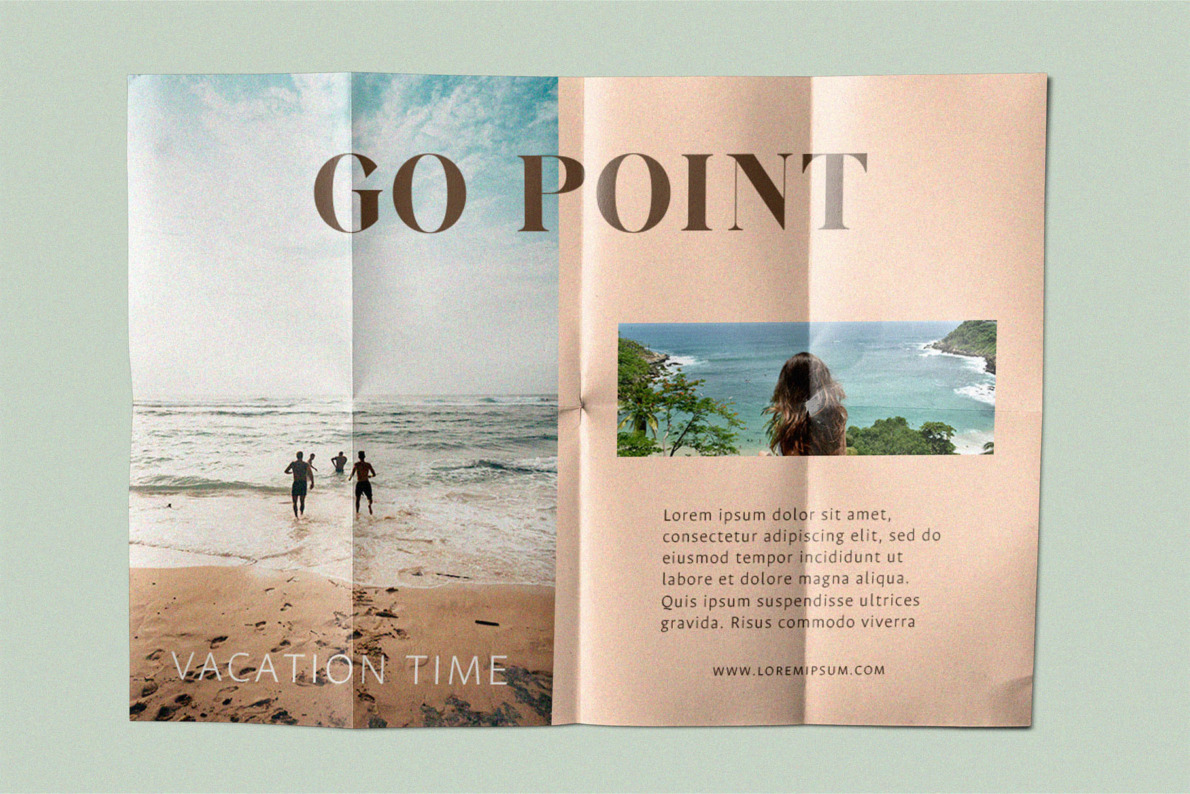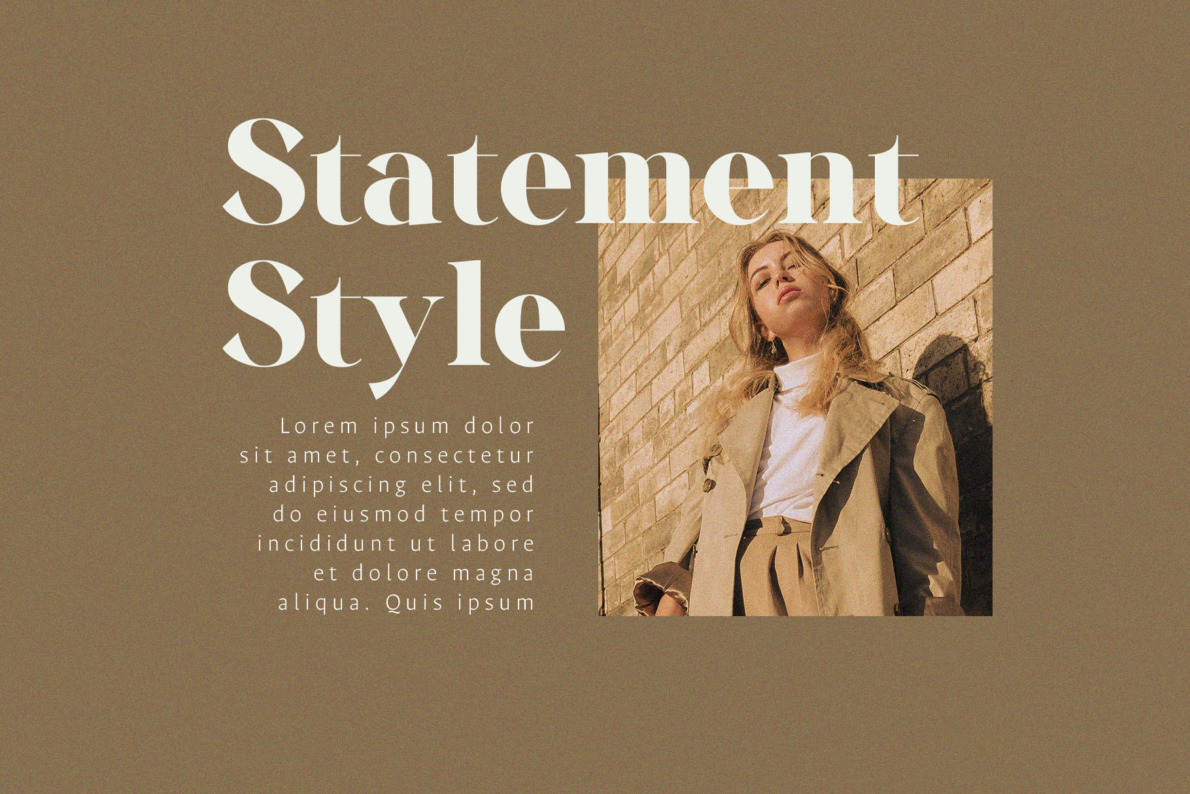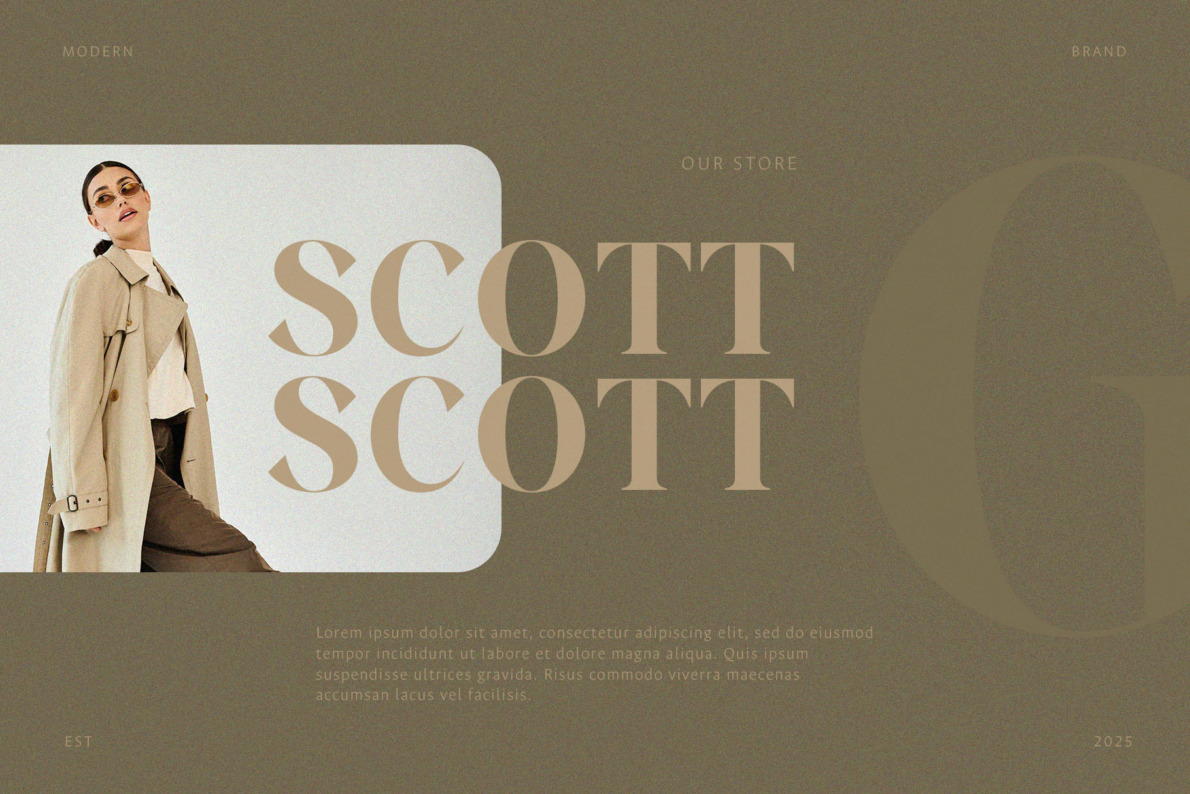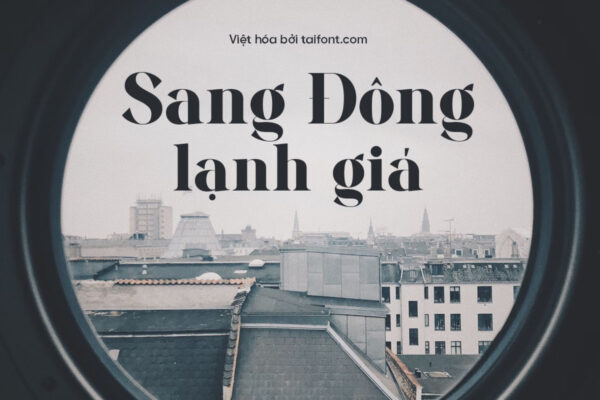
Giới thiệu về Font TF Ceflinty Việt hóa
TF Ceflinty Việt hóa là một font chữ có chân (serif) mang vẻ đẹp tinh tế, hiện đại và rất chuyên nghiệp. Với những đường nét được thiết kế sắc sảo và rõ ràng, font này toát lên sự sang trọng và thanh lịch, đồng thời vẫn đảm bảo tính dễ đọc cao.
Font này là lựa chọn lý tưởng để tạo nên sự ấn tượng và chuyên nghiệp, đặc biệt là trong các ấn phẩm đòi hỏi tính thẩm mỹ và khả năng truyền tải thông điệp rõ ràng:
- Tiêu đề: Hoàn hảo để tạo các tiêu đề chính trên website, báo cáo, bài thuyết trình, hoặc các ấn phẩm in ấn. Nét chữ sắc sảo của Ceflinty giúp tiêu đề nổi bật, thu hút sự chú ý và tạo cảm giác đáng tin cậy.
- Slide trình chiếu: Lý tưởng để sử dụng làm tiêu đề hoặc các điểm nhấn quan trọng trong các bài thuyết trình chuyên nghiệp. Font này sẽ giúp các thông điệp chính trở nên rõ ràng, chuyên nghiệp và có tính thẩm mỹ cao, góp phần tạo nên một bài trình bày ấn tượng.
Với TF Ceflinty Việt hóa, bạn có thể dễ dàng thổi hồn tinh tế và sự chuyên nghiệp vào các thiết kế, tạo ra những sản phẩm không chỉ đẹp mắt mà còn rất hiệu quả trong việc truyền tải thông điệp.
Font Việt hóa TF Ceflinty